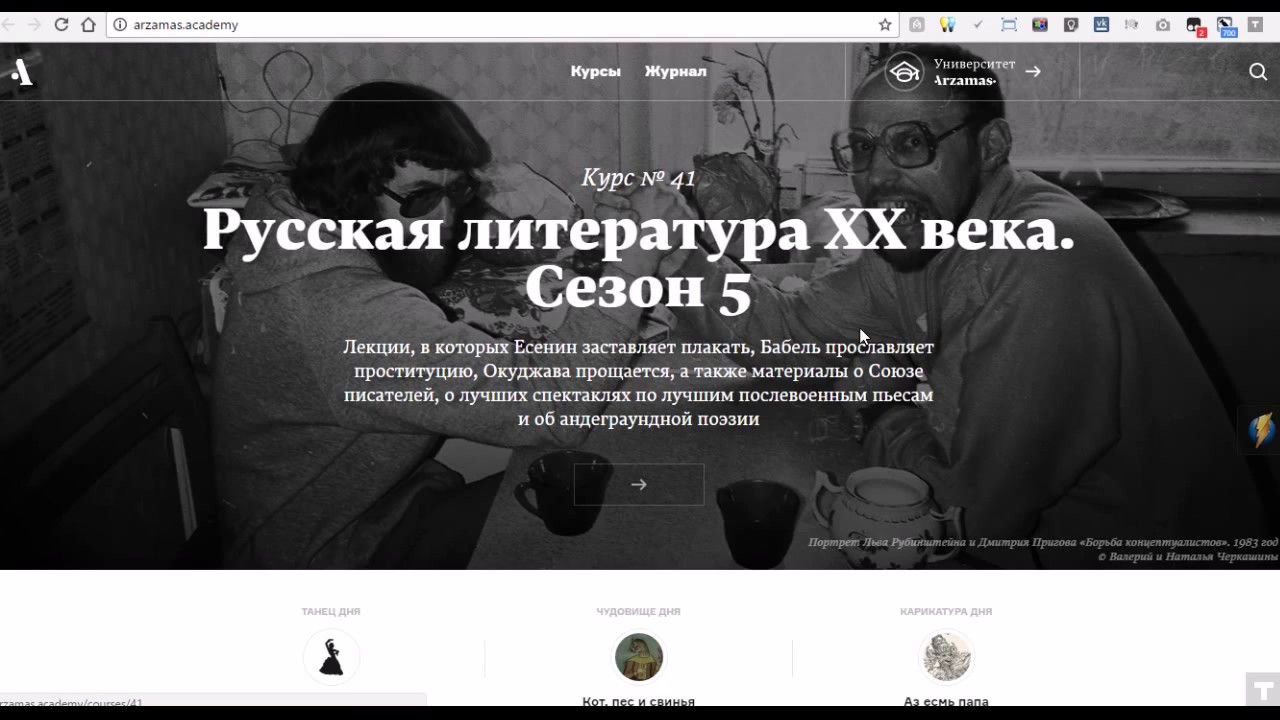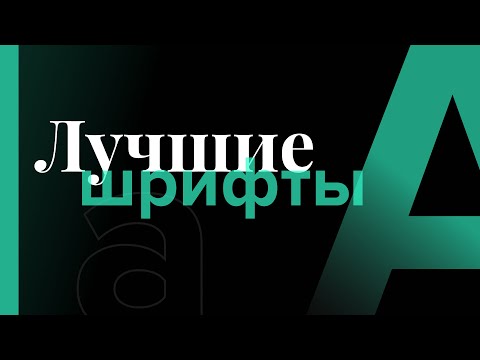
Лучшие способы выбрать шрифт для вашего сайта и не засорить его дизайн
Шрифт является важным элементом дизайна и имеет большое значение для восприятия информации на сайте. В данном материале вы найдете полезные советы и рекомендации по выбору шрифта для вашего сайта, а также советы о том, как сделать его уникальным и запоминающимся.
Изучите целевую аудиторию и назначение сайта, чтобы определиться с настроением и стилем шрифта: серьезный, игривый, минималистичный и т.д.
Рассмотрите несколько вариантов шрифтов и проверьте, как они выглядят на различных устройствах и в разных браузерах.
Создайте комбинацию шрифтов, чтобы добавить глубину и интерес к дизайну сайта. Используйте контрастные шрифты, чтобы сделать акцент на заголовках и основном тексте.